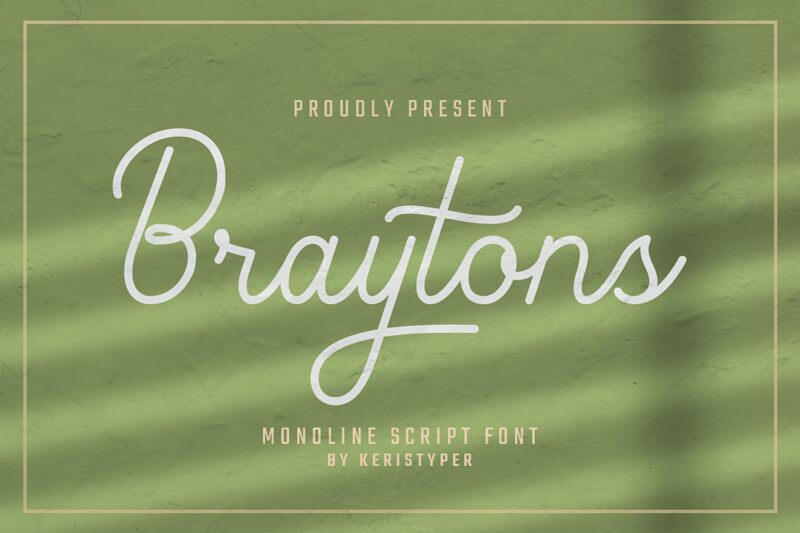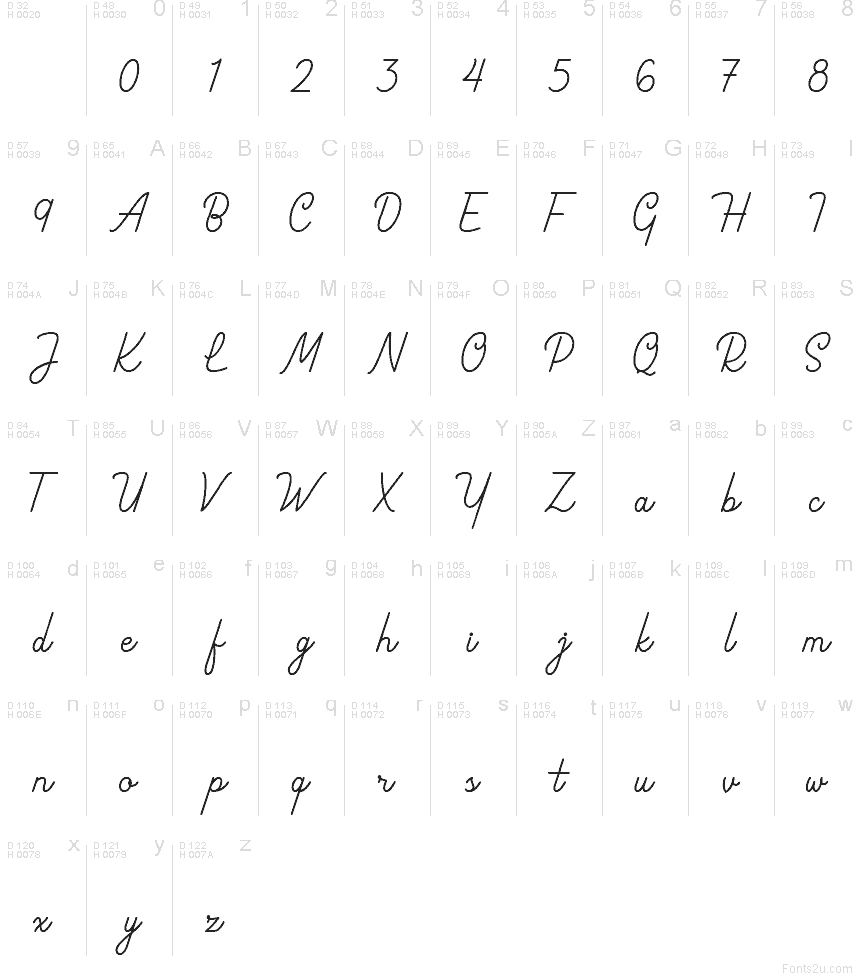
Braytons
Braytons di Keristyper è un font scritto a mano gratuito, caratterizzato da lunghi tratti avvolgenti e un ritmo corsivo rilassato che mantiene le lettere leggere e agili. Il tratto rimane fluido e uniforme, mentre le aste alte e le curve morbide conferiscono alla scrittura una cadenza arieggiata e personale, diversa dalla solita calligrafia formale.
Questo movimento naturale si adatta perfettamente a loghi di boutique, packaging di prodotti, menù di caffè, citazioni per i social media e cancelleria per matrimoni, dove uno stile firma casual aiuta a dare il tono giusto. Può anche dare carattere a brevi titoli o biglietti da visita, soprattutto quando si desidera che i tratti estesi di entrata e uscita incornicino la parola senza bisogno di ulteriori ornamenti.